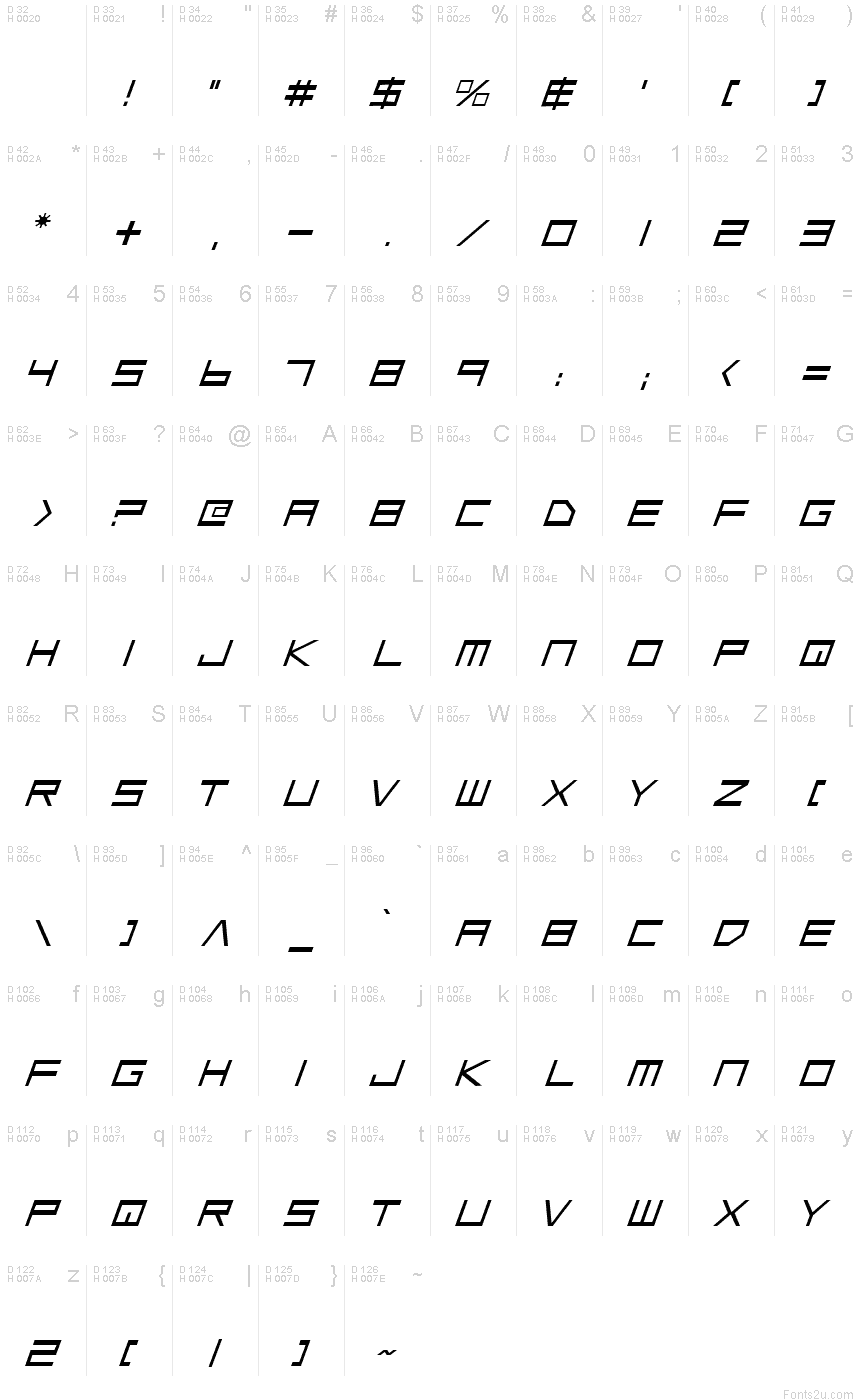
Low Gun Screen Italic, un font display techno in corsivo gratuito del 2007 firmato Iconian Fonts, punta dritto a un mood da corse futuristiche. Le maiuscole sono sezionate in forme ampie e spigolose, con tagli netti e spazi in stile a blocchi, per far sembrare le lettere simili a motion graphic congelate nel movimento piuttosto che a caratteri convenzionali.
È perfetta per loghi di videogiochi, poster sci-fi, branding per e-sport, titoli e copertine che richiedono brevi raffiche di testo con quel tocco veloce e ingegneristico. Essendo un font gratuito, è ideale per titoli, grafiche di schermate di caricamento, merch ispirato alle interfacce e logotipi compatti, poiché la geometria inclinata conferisce anche alle frasi brevi una spinta meccanica carica di energia.
Low Gun Screen Italic